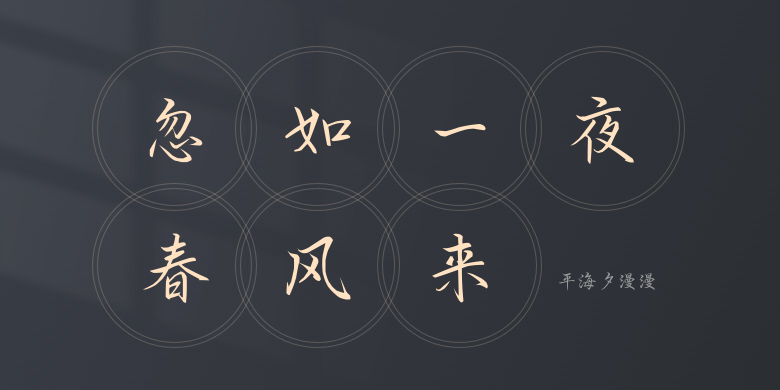
平海夕漫漫
平海夕漫漫,这款字体结构工整、笔画清晰,兼顾美观与易读性,适用于标题、正文、海报、包装、LOGO 等多种场景。字形优雅稳定,风格百搭耐看,适配日常排版与创意设计,让文字呈现更舒适、更具质感。平海夕漫漫一笔一画,皆是细节,以均衡的比例、流畅的线条打造舒适视觉体验,字形端正大气,风格简约现代。无论是商业设计、品牌宣传还是日常排版,都能轻松驾驭,让文字更有格调与力量。平海夕漫漫字体下载。